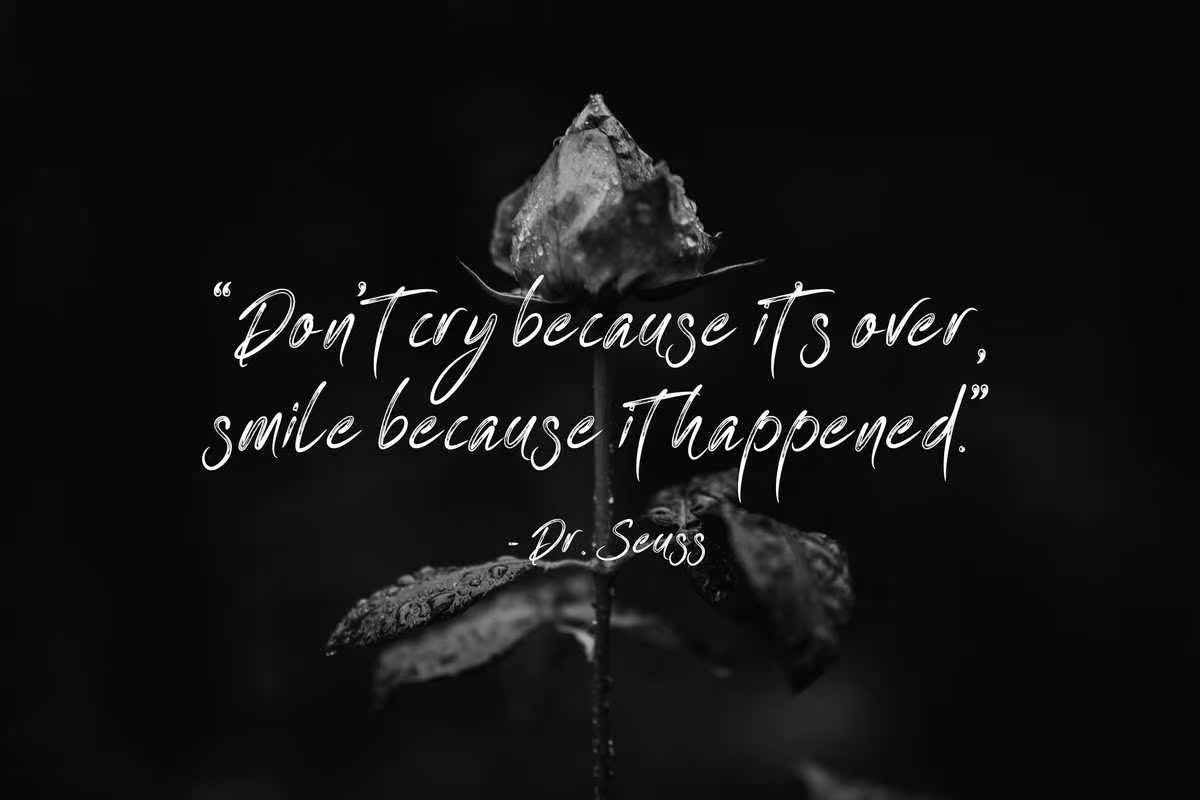
一件是RushScript字体。它优雅、优雅、吸引人、易读且酷。这种字体完美地包容了您的品牌项目、时尚、服装项目和GothVibe,但也适用于其他项目,如海报、包装、广告、标题、社交媒体、品牌,标志和任何你想要的城市外观和感觉的东西。一件是RushScript字体。它优雅、经典、吸引人、易读且酷。这种字体完美地原谅了你的品牌项目,时尚、服装项目的字体和GothVibe,但也适用于其他项目,如海报、包装、广告、头条、社交媒体、品牌,标志和任何你想要城市外观和感觉的东西。